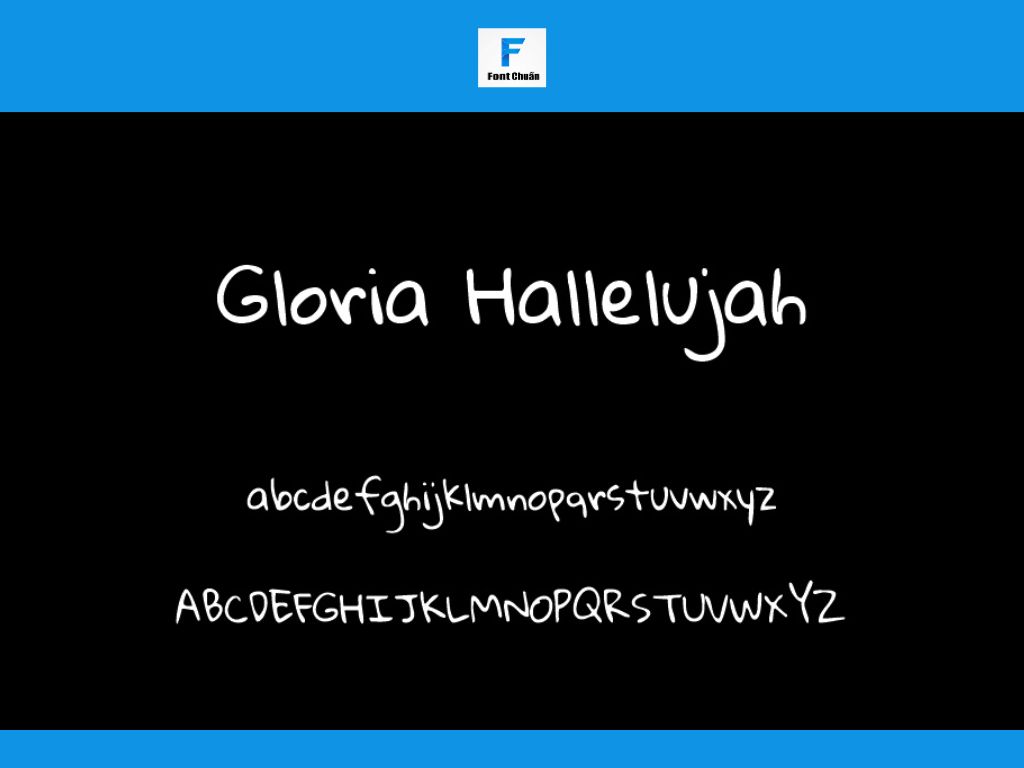
Bạn đang tìm kiếm các font hoạt hình đẹp để làm thiết kế thêm sinh động? Bài viết này tổng hợp 77+ font chữ hoạt hình miễn phí, dễ tải xuống và sử dụng ngay. Từ poster, banner đến digital content, tất cả đều có font phù hợp cho mọi dự án sáng tạo.
Phân loại font hoạt hình phổ biến
Font chữ kiểu hoạt hình có nhiều phong cách khác nhau, phù hợp với từng loại thiết kế và đối tượng người xem. Việc hiểu rõ các loại font phổ biến sẽ giúp bạn chọn lựa đúng font, tạo ra các thiết kế sinh động và ấn tượng. Dưới đây là ba nhóm font chữ kiểu hoạt hình phổ biến:
Font chữ hoạt hình dạng cartoon
Font chữ dạng cartoon nổi bật với nét chữ tròn, mềm mại và vui nhộn, mang đến cảm giác thân thiện, dễ nhìn và dễ nhớ. Đây là lựa chọn lý tưởng cho các thiết kế giải trí, poster, banner hoặc nội dung dành cho trẻ em. Các font chữ dạng cartoon nổi bật bao gồm:
- Comic Sans: dễ đọc, vui nhộn, phù hợp trẻ em.
- Baloo: nét chữ tròn trịa, hiện đại và thân thiện.
- Fredoka One: uyển chuyển, nổi bật, tạo điểm nhấn cho tiêu đề.
Font hoạt hình dạng fantasy/magical
Font chữ dạng fantasy hoặc magical mang phong cách phép thuật, cổ tích, rất thích hợp cho sách truyện thiếu nhi, poster phim hoạt hình hoặc thiết kế mang yếu tố kỳ ảo. Những font này thường có các chi tiết uốn lượn, tạo cảm giác huyền bí, ma thuật.
Ví dụ:
- Magic School: tạo cảm giác thần tiên, phù hợp truyện cổ tích.
- Storybook: cổ điển, mềm mại, mang hơi hướng truyện kể.
Font hoạt hình dạng handwritten
Font chữ handwritten giả lập chữ viết tay, tạo cảm giác gần gũi, tự nhiên và thân thiện. Chúng phù hợp với thiết kế mang tính cá nhân, giáo dục hoặc các dự án cần sự ấm áp, vui vẻ. Một số ví dụ phổ biến:
- KG Happy: chữ mềm mại, vui nhộn, phù hợp trẻ em.
- Chalkboard SE: mô phỏng bảng viết phấn, tạo cảm giác học đường, sinh động.
Top 77+ font chữ hoạt hình miễn phí và chất lượng
Để thiết kế trở nên sinh động và thu hút, việc chọn font hoạt hình phù hợp là rất quan trọng. Dưới đây là danh sách 15 font chữ trong hoạt hình miễn phí phổ biến, kèm mô tả chi tiết và gợi ý sử dụng:
Font hoạt hình việt hoá dùng cho in ấn
Comic Sans
Comic Sans là font chữ tròn trịa, vui nhộn và cực kỳ dễ đọc. Nó mang lại cảm giác thân thiện, gần gũi và thường được dùng trong sách thiếu nhi hoặc poster quảng cáo. Nhờ nét chữ đơn giản, Comic Sans rất phù hợp với các thiết kế cần truyền tải thông điệp rõ ràng nhưng vẫn vui tươi. Đây cũng là font phổ biến cho các ấn phẩm in ấn dành cho trẻ em.
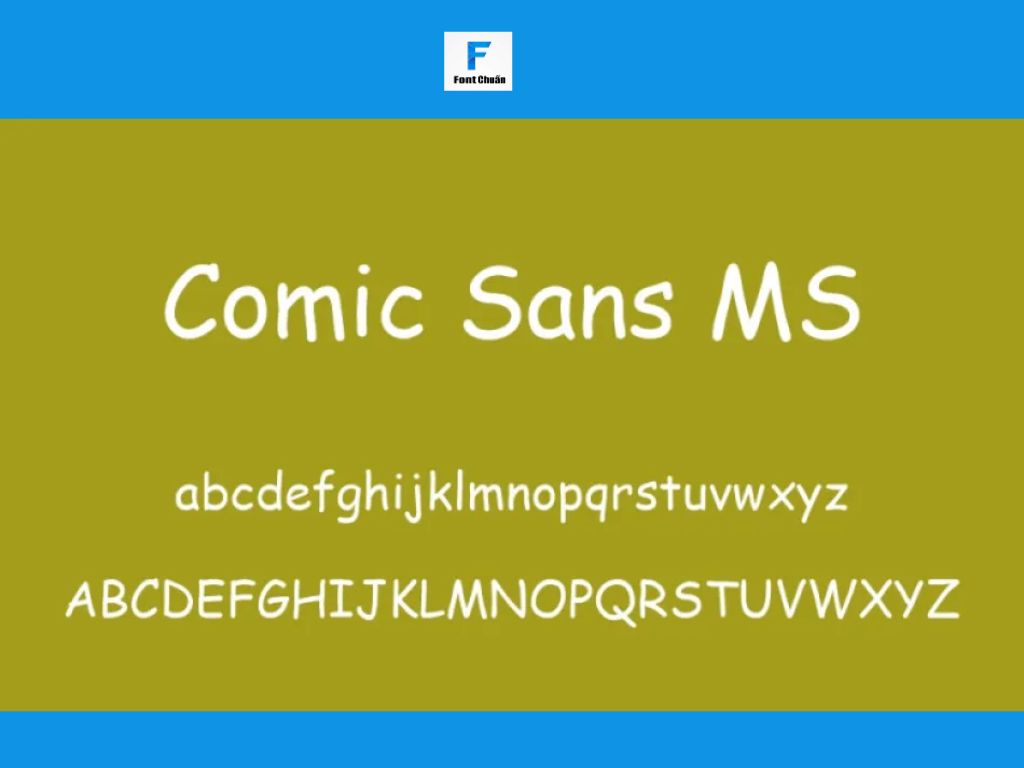
Fredoka One
Fredoka One có các nét chữ mềm mại, dày và uyển chuyển, tạo cảm giác vui nhộn ngay từ cái nhìn đầu tiên. Font này nổi bật, dễ đọc và thường được dùng cho tiêu đề trên poster, bìa sách hay banner in ấn. Nhờ đường nét tròn trịa, Fredoka One mang lại sự thân thiện và sinh động cho các thiết kế.
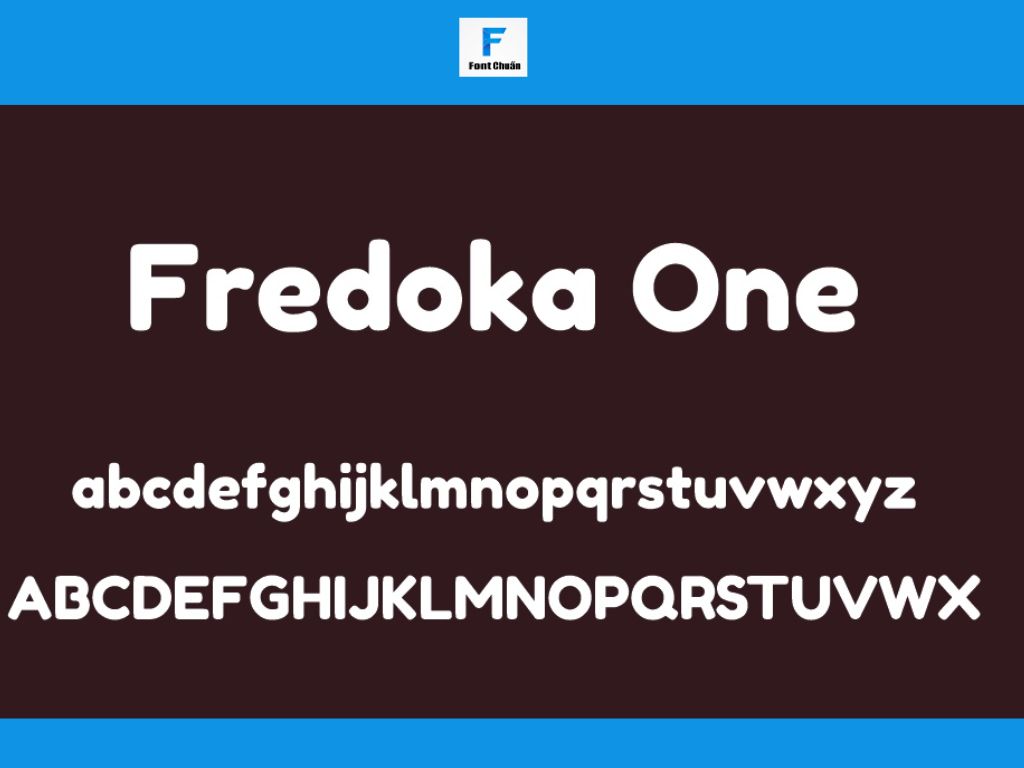
Baloo 2
Baloo 2 là font chữ đậm, tròn, mang phong cách năng động và hài hước. Font này thích hợp làm tiêu đề trên tờ rơi, banner hoặc sách thiếu nhi, nhấn mạnh thông điệp một cách vui vẻ. Đặc điểm nổi bật của Baloo 2 là vừa mềm mại vừa có cá tính riêng, khiến thiết kế trở nên đáng nhớ.
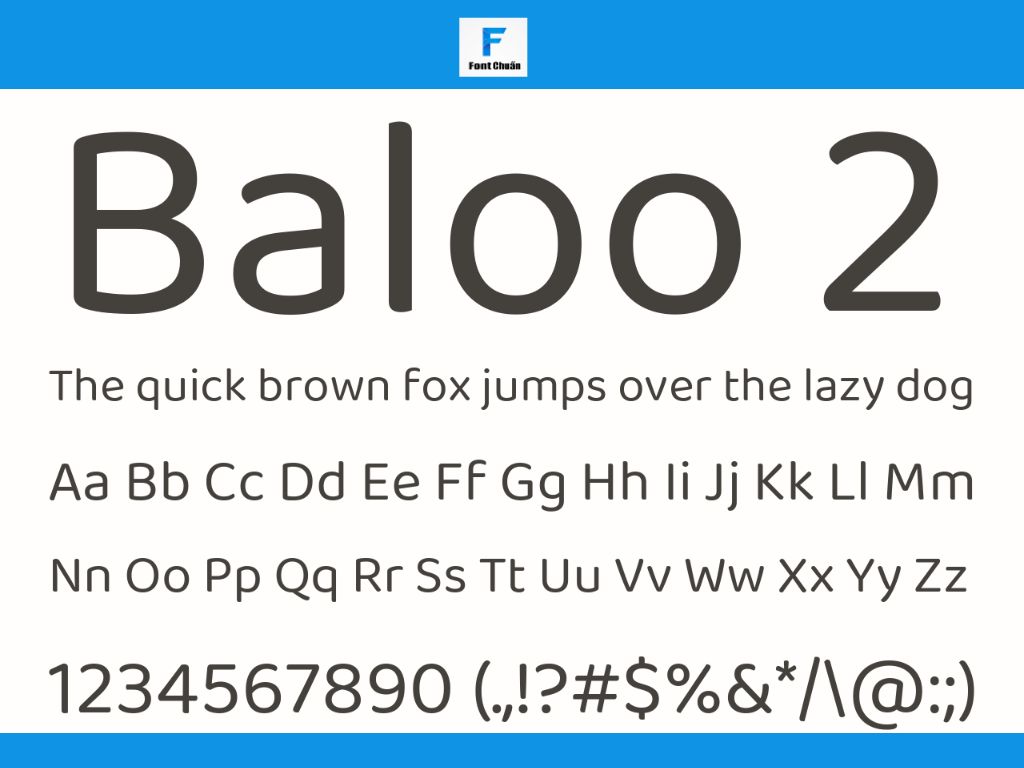
KG Happy
KG Happy mô phỏng chữ viết tay, mang đến cảm giác vui tươi, gần gũi và tự nhiên. Font này rất phù hợp cho bìa sách, nhãn dán hoặc các thiết kế in ấn dành cho trẻ em. Nét chữ mềm mại và uyển chuyển giúp truyền tải thông điệp một cách sinh động và đáng yêu.
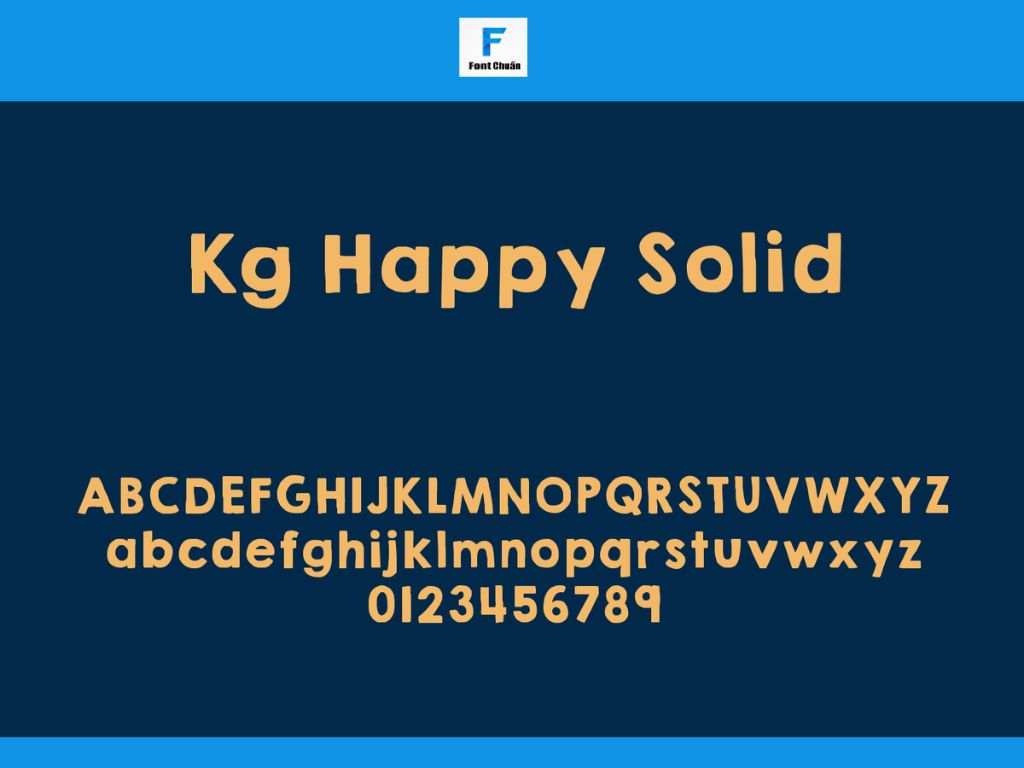
Font chữ hoạt hình cho digital (trang web, social media, video)
Luckiest Guy
Luckiest Guy là font chữ đậm, vui nhộn và mang phong cách comic đặc trưng. Nó rất nổi bật trên hình ảnh số, banner quảng cáo và các video social media. Font này giúp thiết kế trở nên sinh động, hài hước, thu hút sự chú ý của người xem ngay lập tức.
Bangers
Bangers mang phong cách năng động, vui tươi, với các nét chữ cong tròn và dày dặn. Font này thường được dùng trong quảng cáo digital, social media post hoặc thiết kế web trẻ trung. Nhờ nét chữ mạnh mẽ, Bangers dễ dàng tạo điểm nhấn trực quan cho nội dung số.
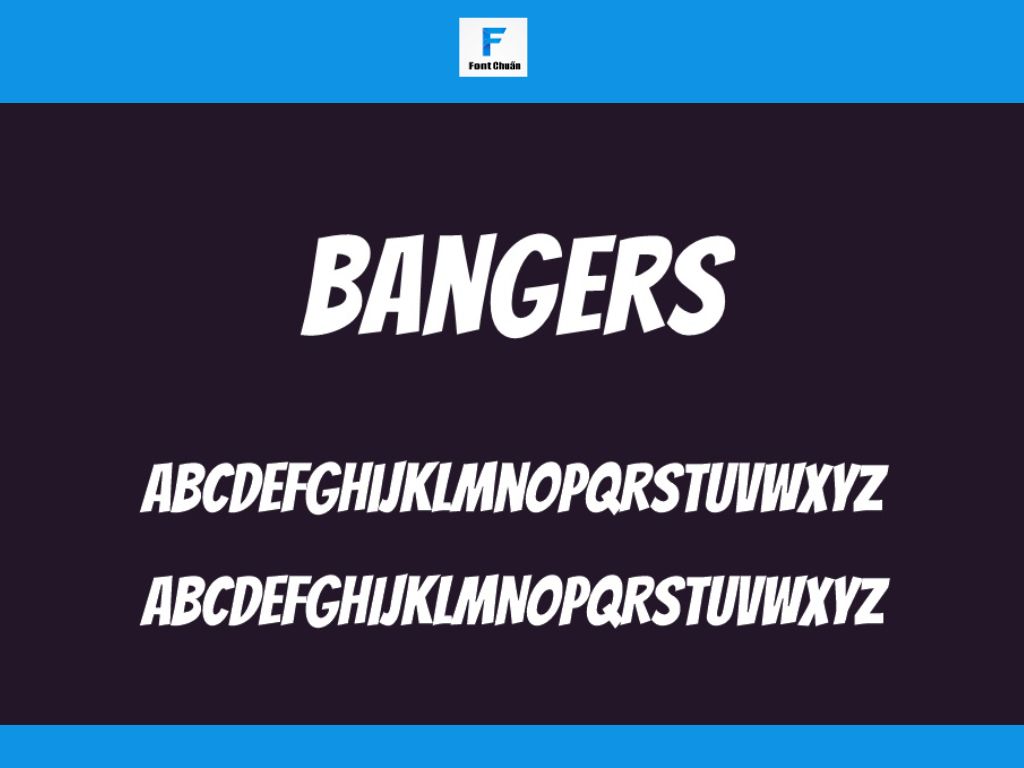
Fredoka One (Digital)
Fredoka One trên digital hiển thị rất rõ nét, mềm mại và thân thiện trên màn hình. Nó phù hợp với banner, infographic, poster online hoặc social media content. Font này vừa giữ được sự vui nhộn của font in ấn, vừa đảm bảo dễ đọc trên các thiết bị số.
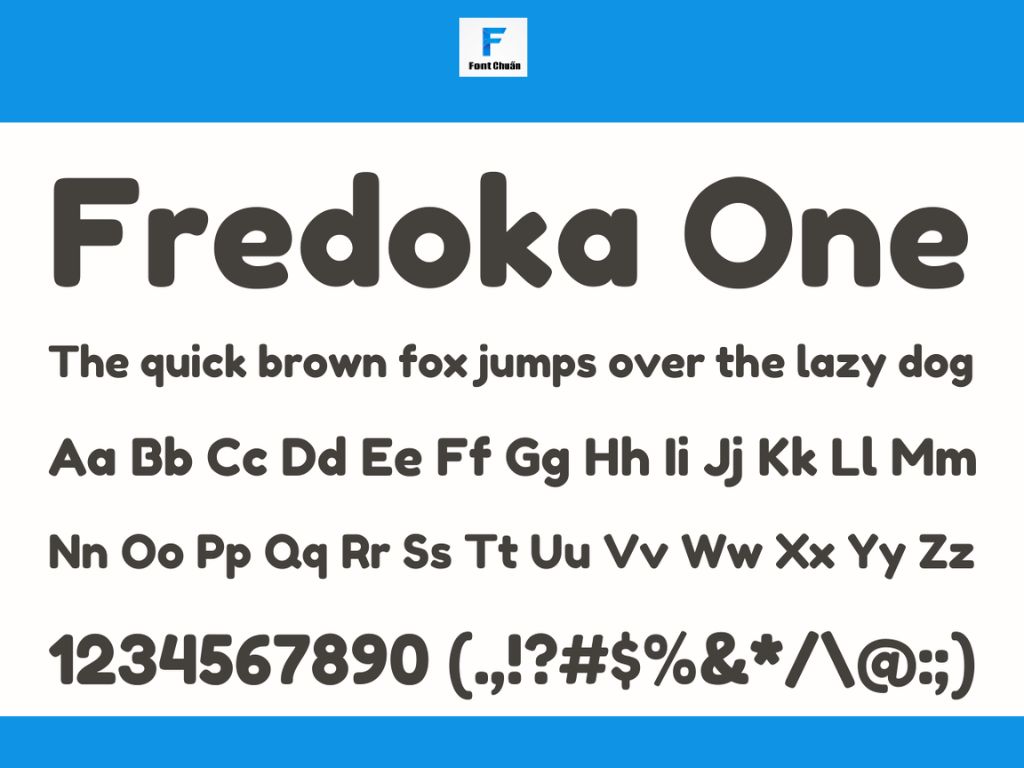
Chewy
Chewy là font chữ mềm mại, uyển chuyển, rất thích hợp với các thiết kế minh họa dành cho trẻ em. Nó mang lại cảm giác vui nhộn và gần gũi, giúp nội dung digital trở nên sinh động. Chewy thường được dùng trong video, banner và poster online để thu hút trẻ em.
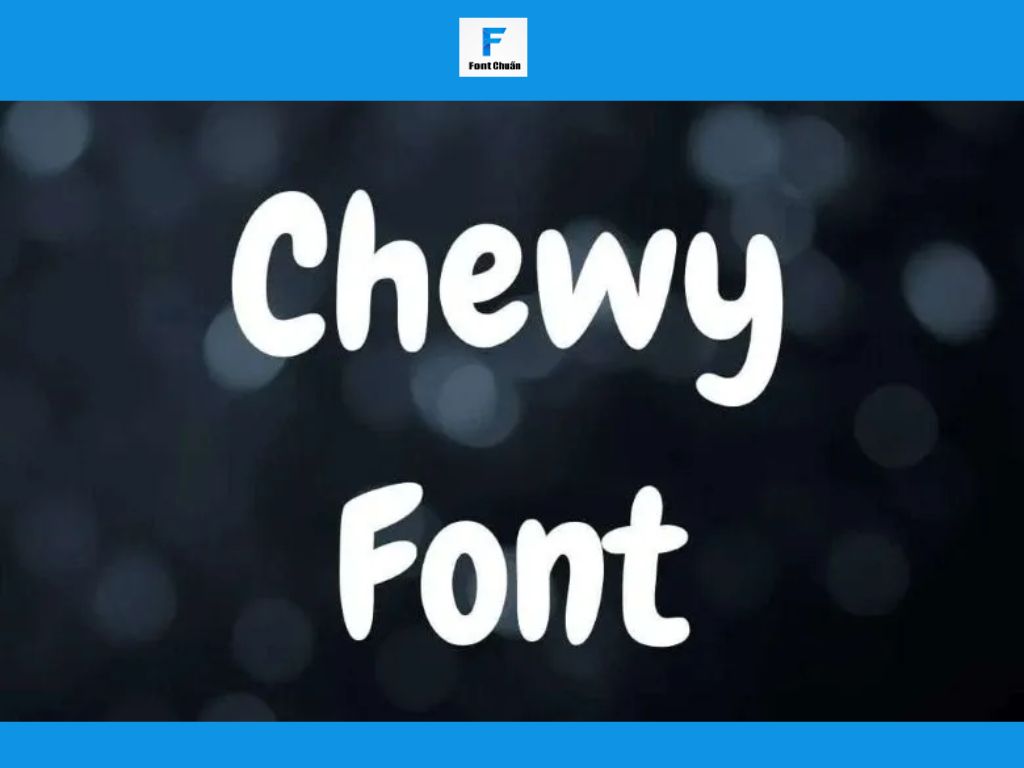
Font chữ hoạt hình free cho web
Baloo (Web)
Baloo hiển thị rất tốt trên mọi trình duyệt, có thể dùng cho cả tiêu đề và nội dung chính. Nét chữ tròn, đậm và năng động giúp website trở nên vui tươi, thân thiện. Font này đặc biệt phù hợp cho các trang web giáo dục hoặc blog dành cho trẻ em.
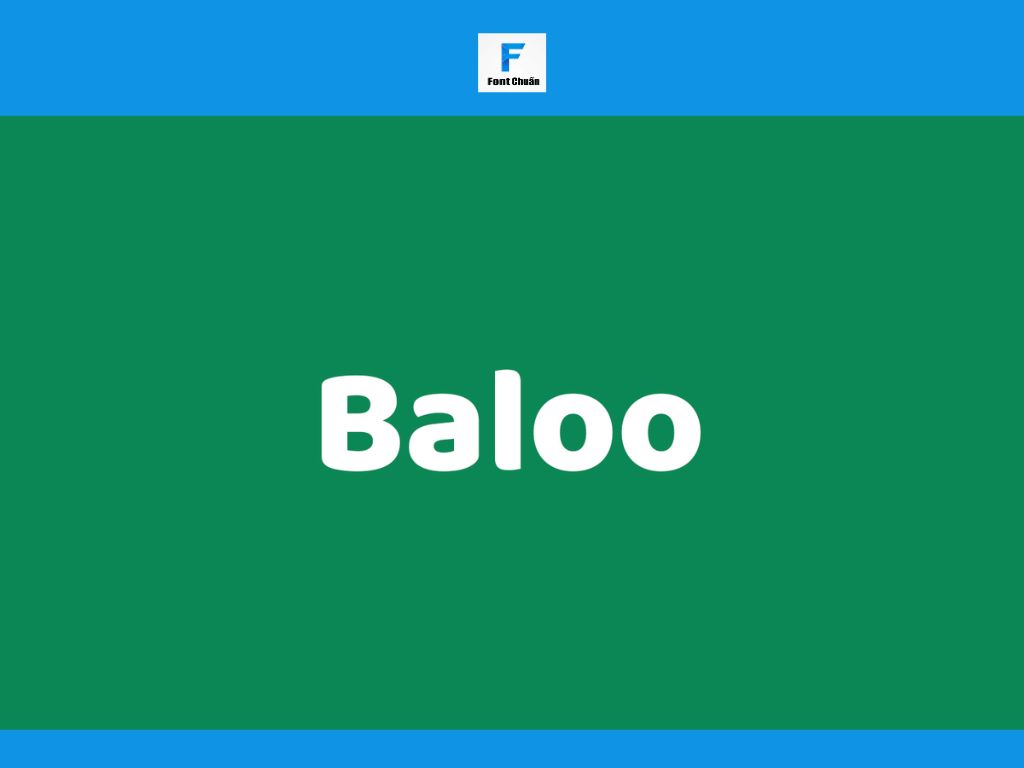
Cabin Sketch
Cabin Sketch mô phỏng chữ viết tay, mang phong cách trẻ trung, gần gũi và tự nhiên. Font này rất thích hợp cho website giáo dục, blog trẻ em hoặc các dự án cần sự ấm áp. Cabin Sketch giúp nội dung web trở nên sinh động, vui nhộn mà vẫn dễ đọc.
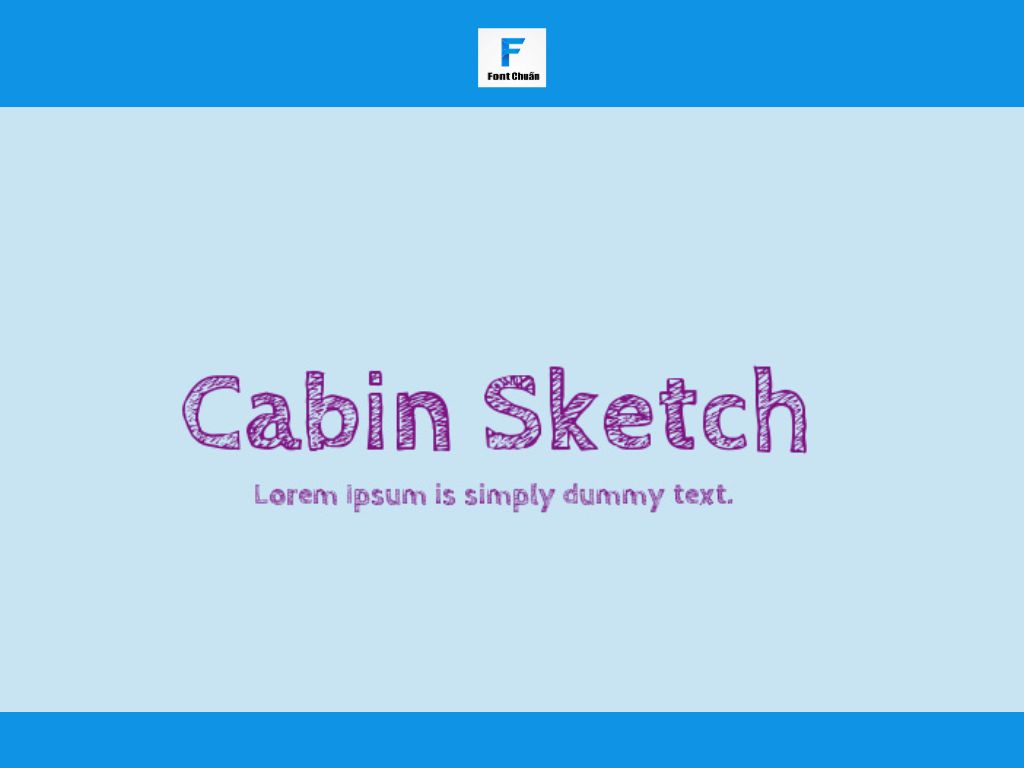
Kiểm tra độ đọc được khi in và trên màn hình
Một font hoạt hình đẹp chưa chắc đã dễ đọc trên mọi nền tảng. Trước khi hoàn thiện thiết kế, hãy kiểm tra khả năng đọc khi in ra giấy và hiển thị trên màn hình. Đảm bảo font chữ rõ ràng, không quá nhỏ hoặc rối mắt, để người xem dễ dàng tiếp nhận thông điệp.
Với danh sách 77+ font chữ hoạt hình miễn phí, bạn có thể thỏa sức sáng tạo. Chỉ cần tải về và áp dụng, thiết kế của bạn sẽ trở nên vui nhộn và thu hút hơn. Hãy chọn font yêu thích và biến mọi dự án thành những sản phẩm độc đáo, sinh động.